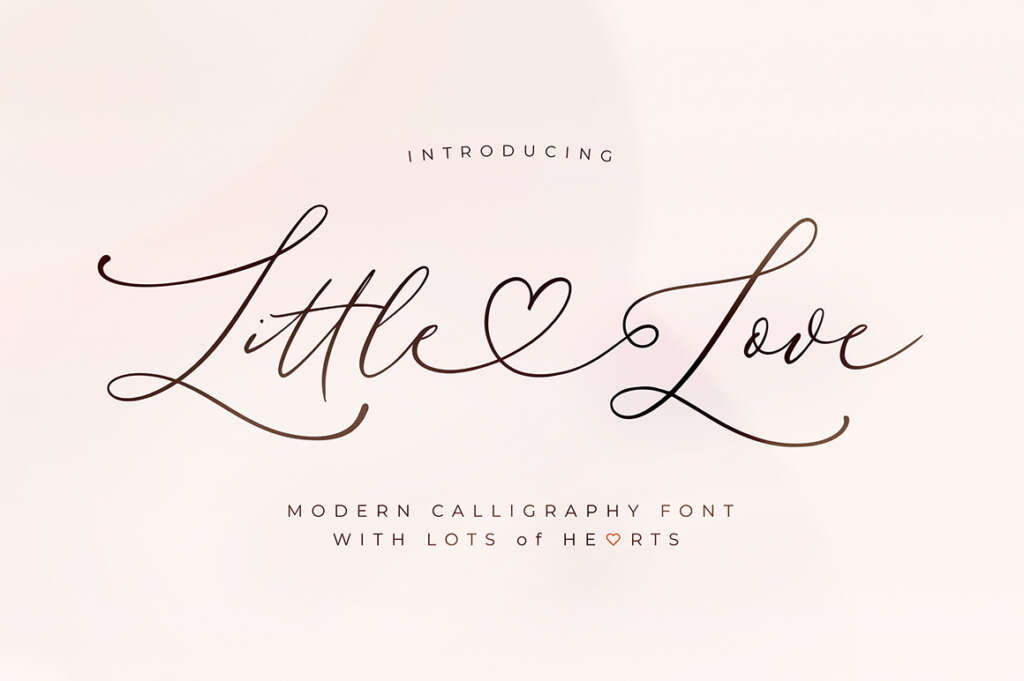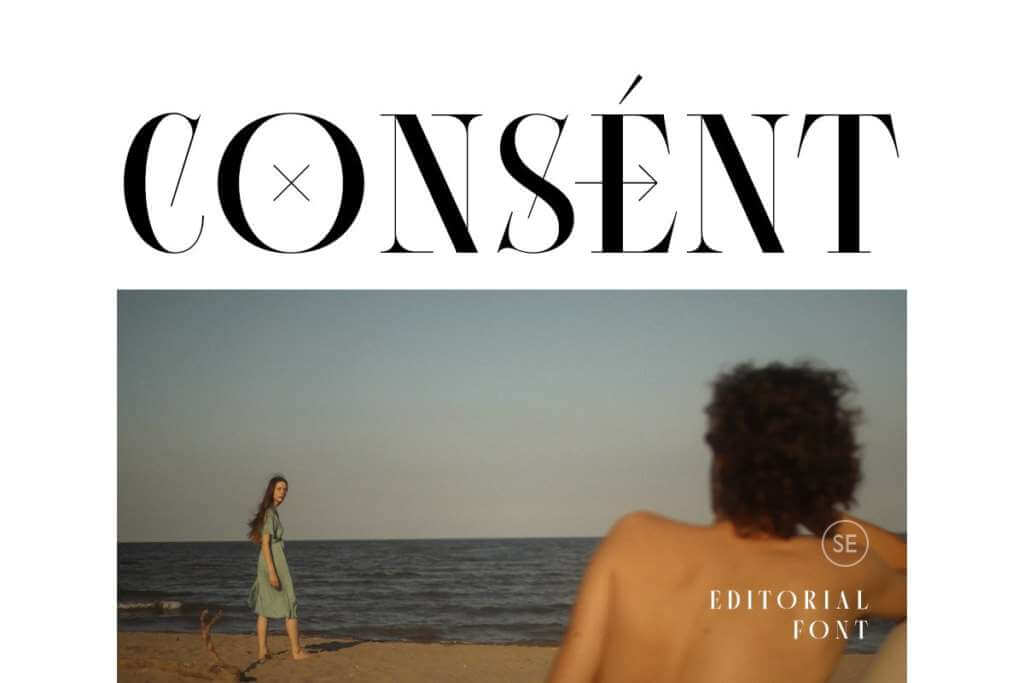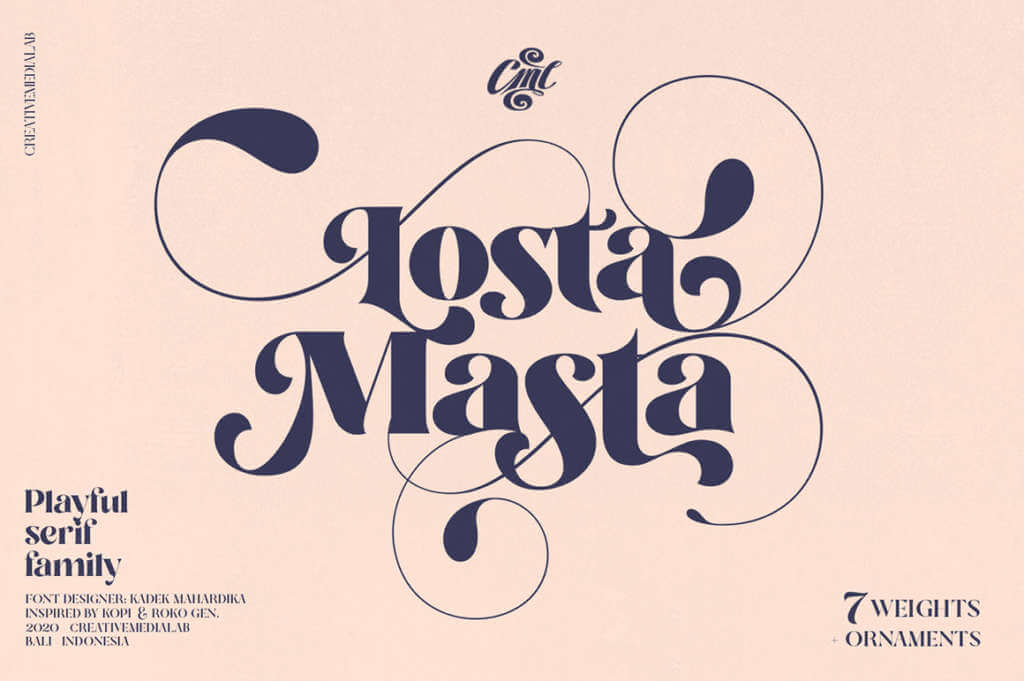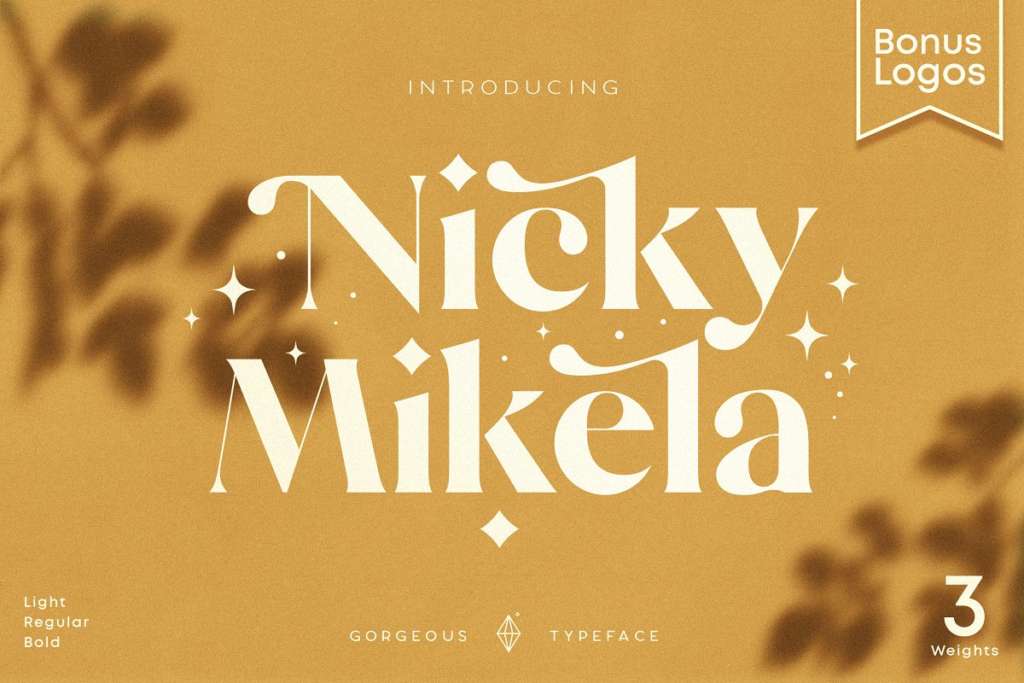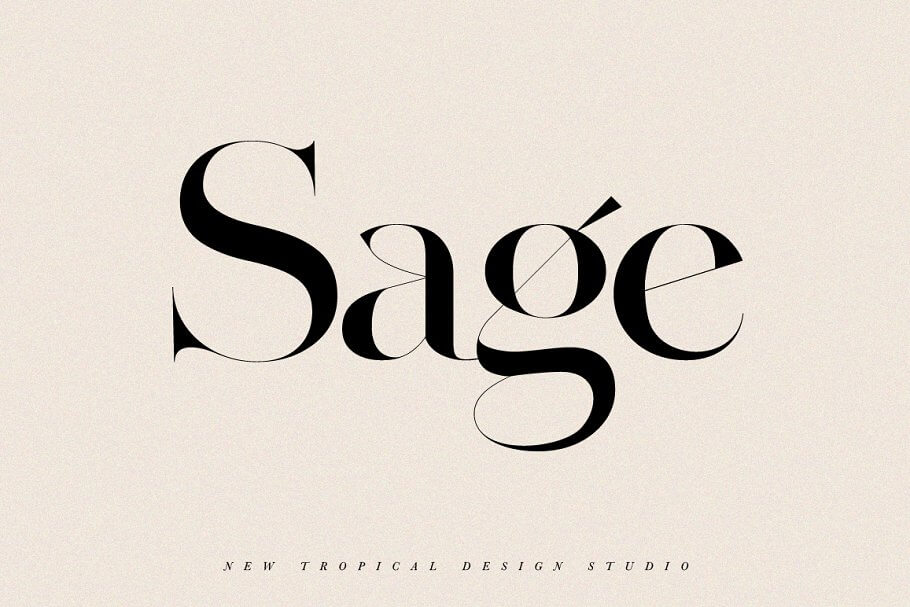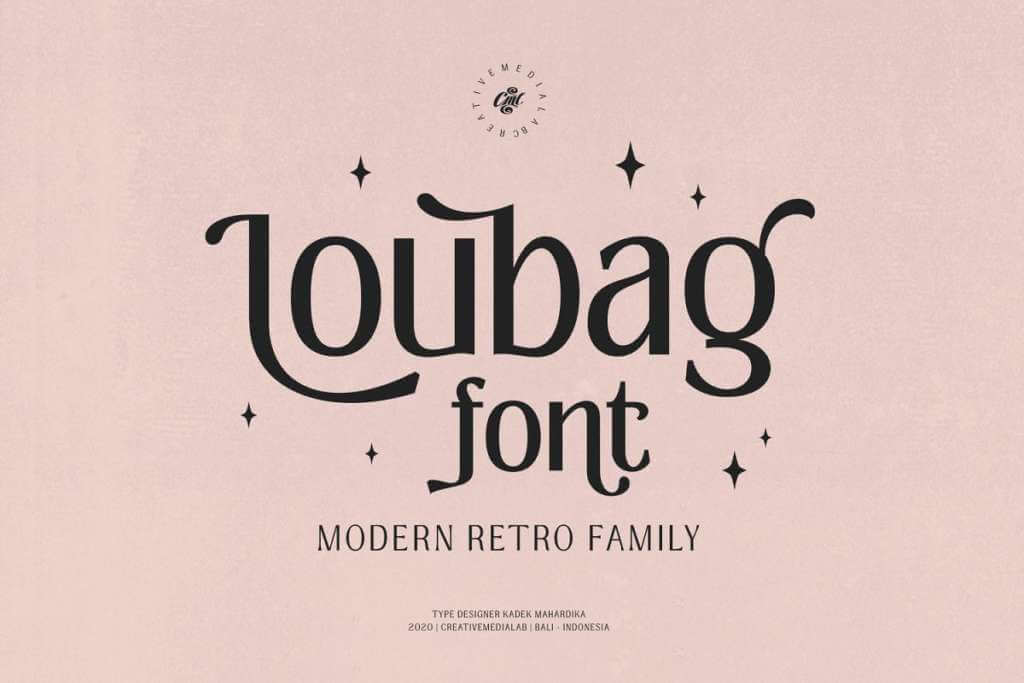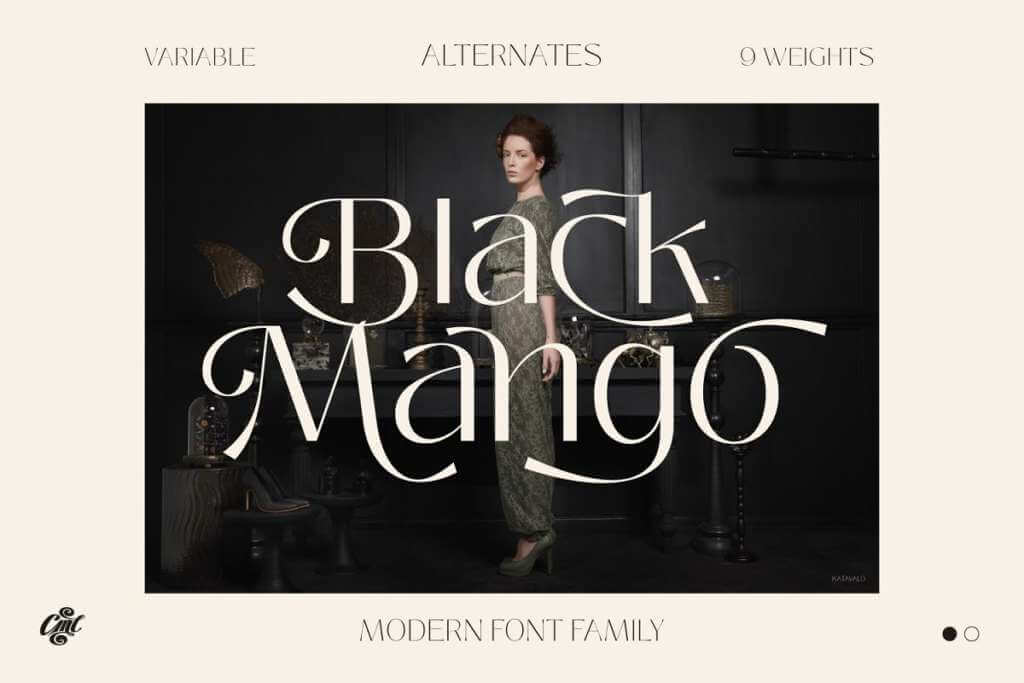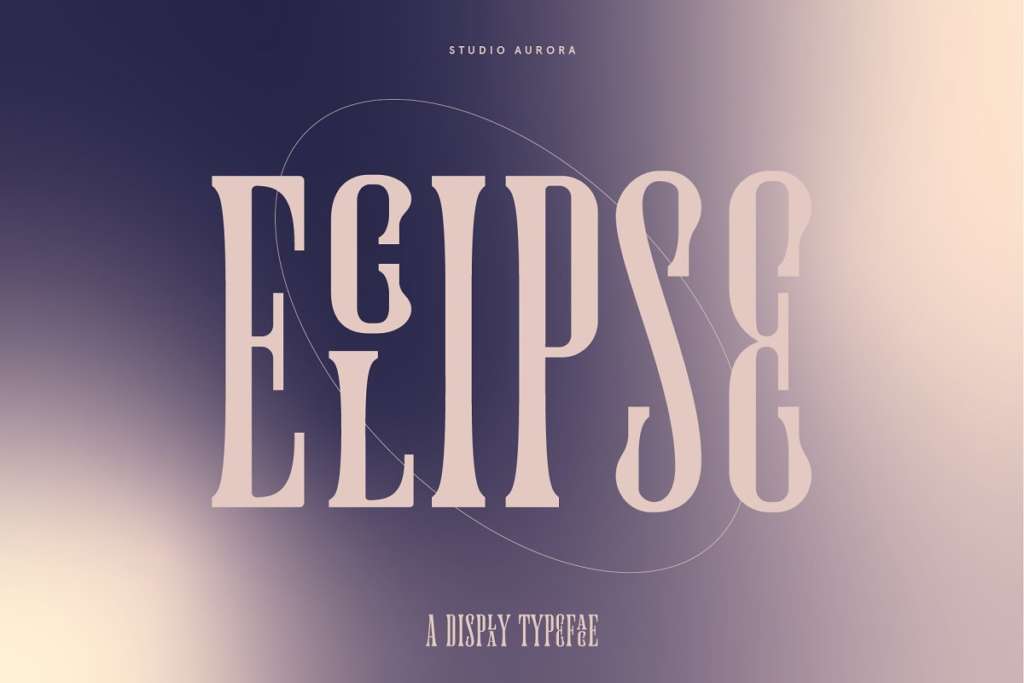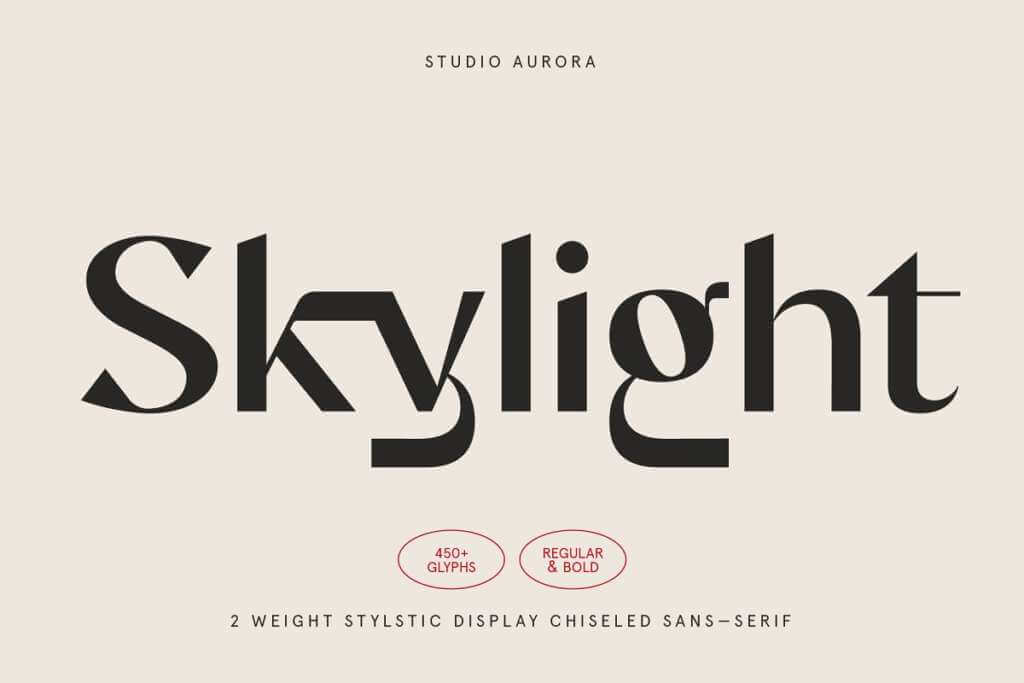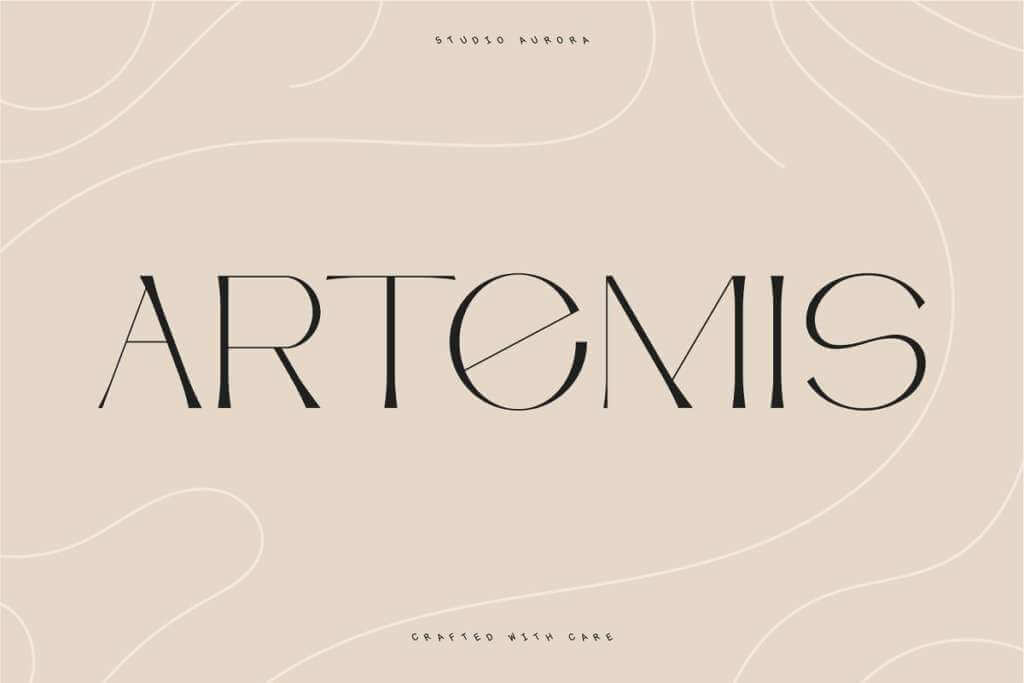
いま使いたい!おしゃれな旬の英語デザインフォント
本記事では、今だからこそ使いたい欧文デザインフォントを紹介します。ポスターやラベルのデザイン、SNSの投稿画像などをおしゃれに仕上げたい時に活躍するフォントばかりです。
では、さっそくみていきましょう。
いま使いたい!おしゃれな旬の英語デザインフォント